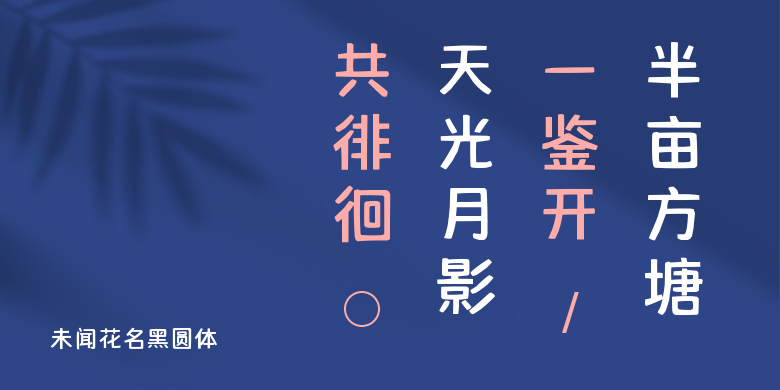
未闻花名黑圆体
未闻花名黑圆体,这款字体结构工整、笔画清晰,兼顾美观与易读性,适用于标题、正文、海报、包装、LOGO 等多种场景。字形优雅稳定,风格百搭耐看,适配日常排版与创意设计,让文字呈现更舒适、更具质感。未闻花名黑圆体一笔一画,皆是细节,以均衡的比例、流畅的线条打造舒适视觉体验,字形端正大气,风格简约现代。无论是商业设计、品牌宣传还是日常排版,都能轻松驾驭,让文字更有格调与力量。未闻花名黑圆体字体下载。